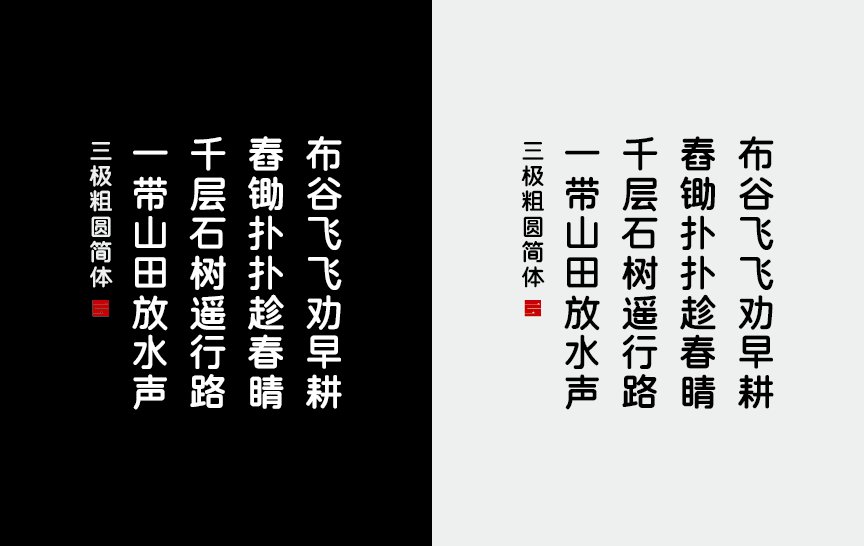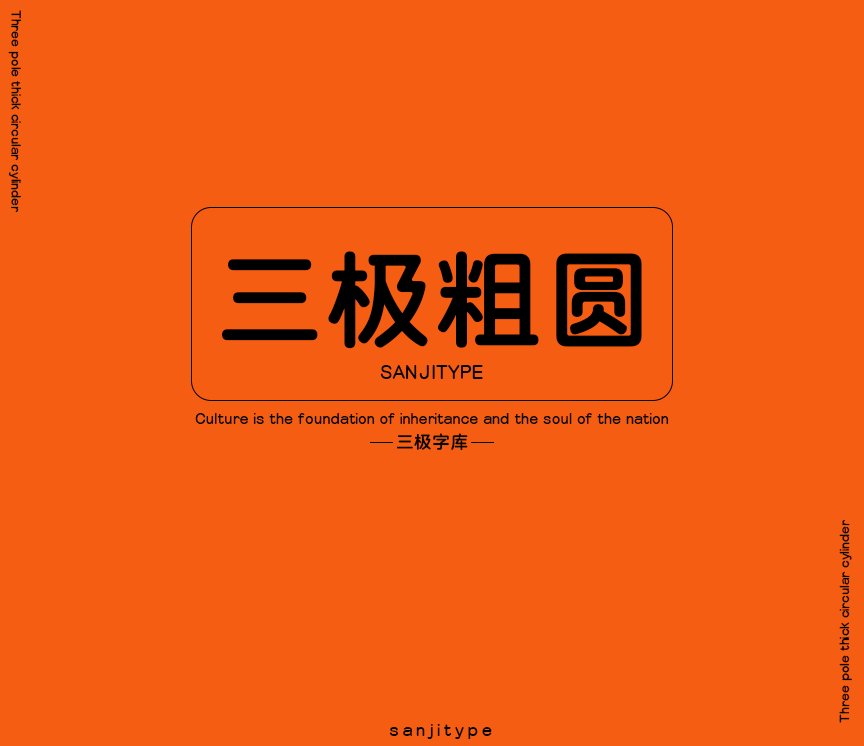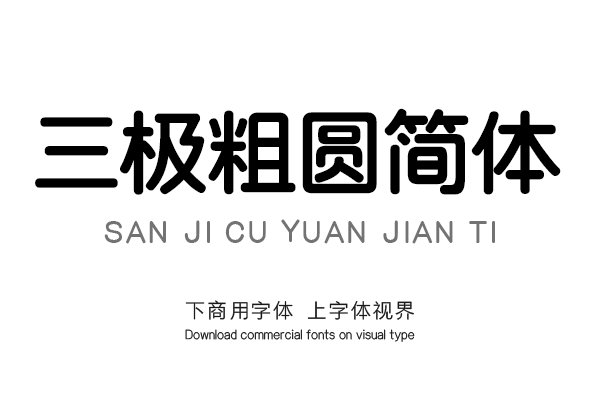
三极粗圆简体是一款家族字体,字形稳重,结构严谨,字面较大。起笔收笔处为圆形,折笔圆弧,撇捺外延、增强了字体的识别性,字形更加圆润大气。适用于各类便携式屏幕的系统......购买须知:“下载服务费”与“字体VIP”所获得字体 仅用于个人非商用, 商用请联系付费授权。本字体为电脑用字,手机没有root权限不支持直接手机换字(手机如何root,请自行百度搜索教程)。购买前请先 了解清楚后再付款 ,字体为虚拟产品无法回收 一旦购买不支持退款。